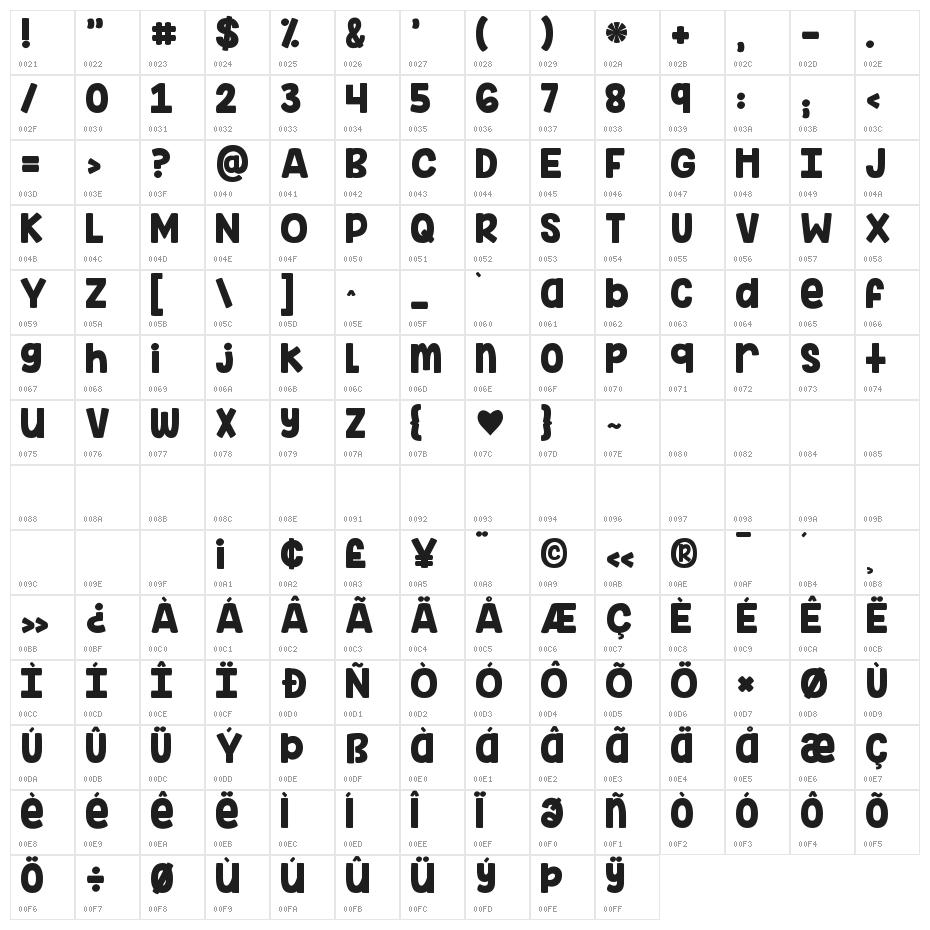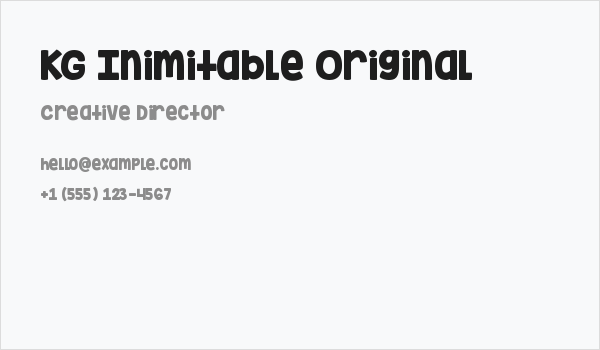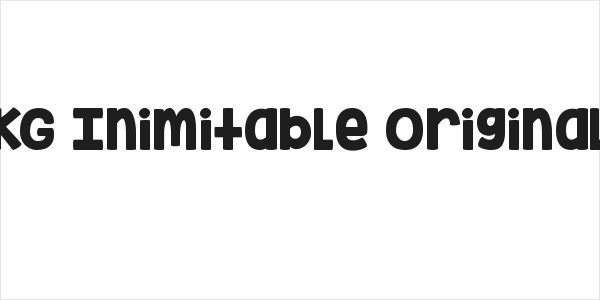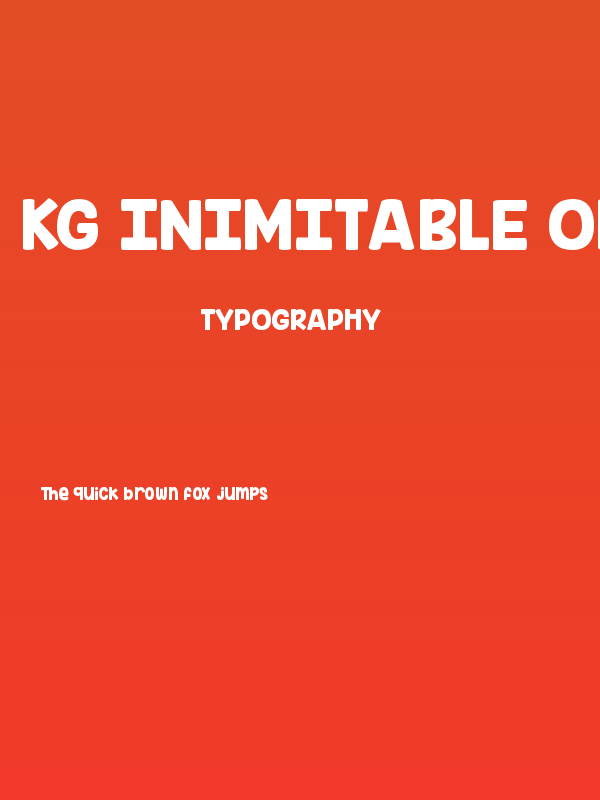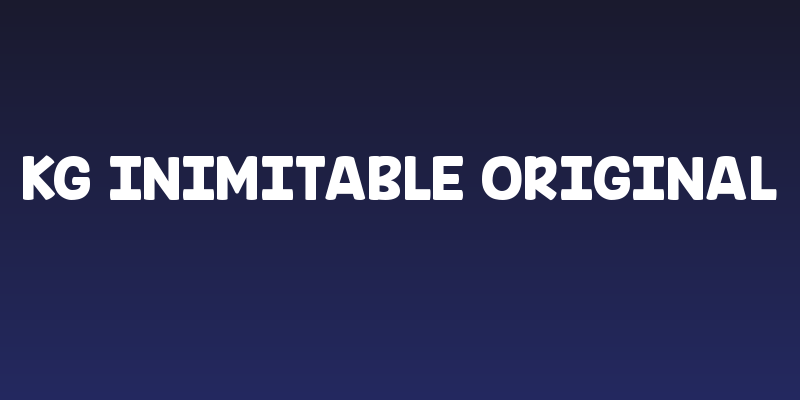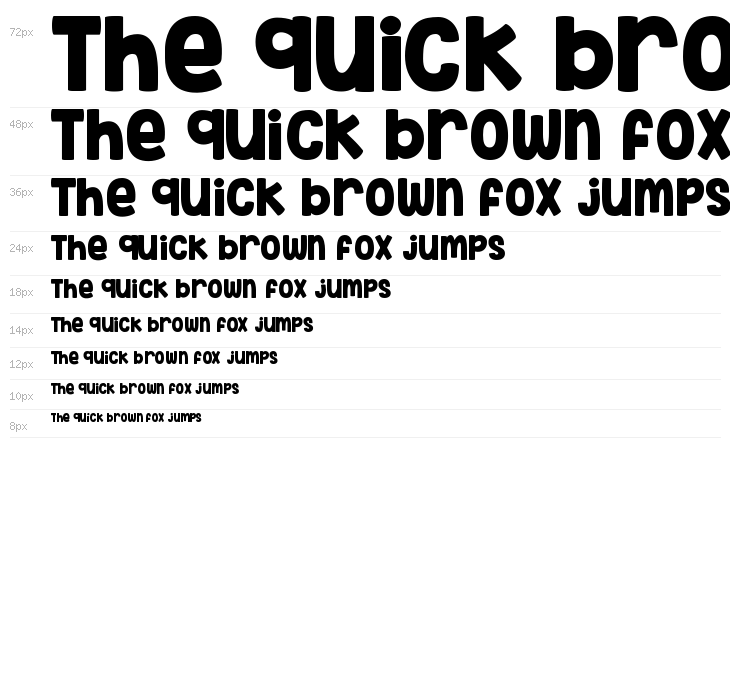
KG Inimitable Original Font
| Stile generale | Playful, Modern |
| Progetti proposti | Ideal for children's books, playful branding, posters, and creative projects that require a friendly and bold typeface. |